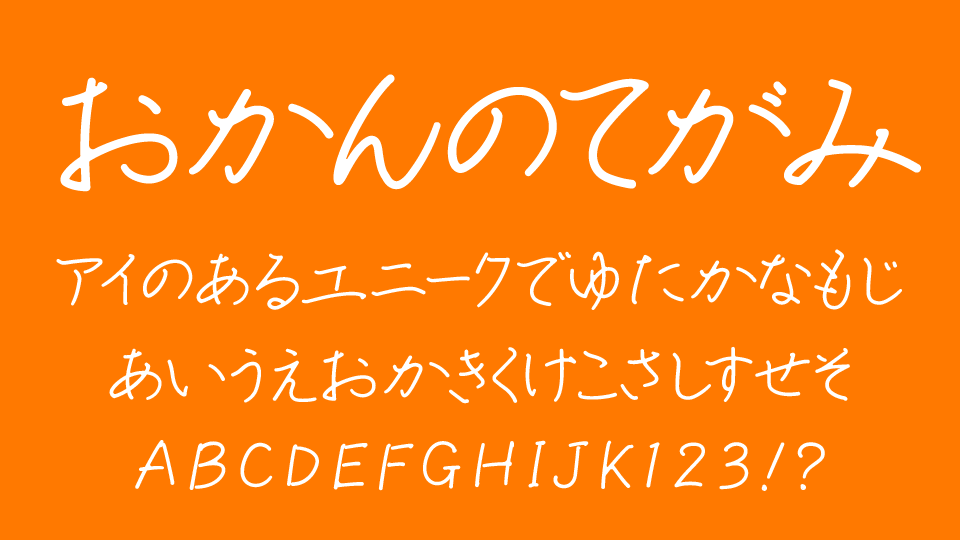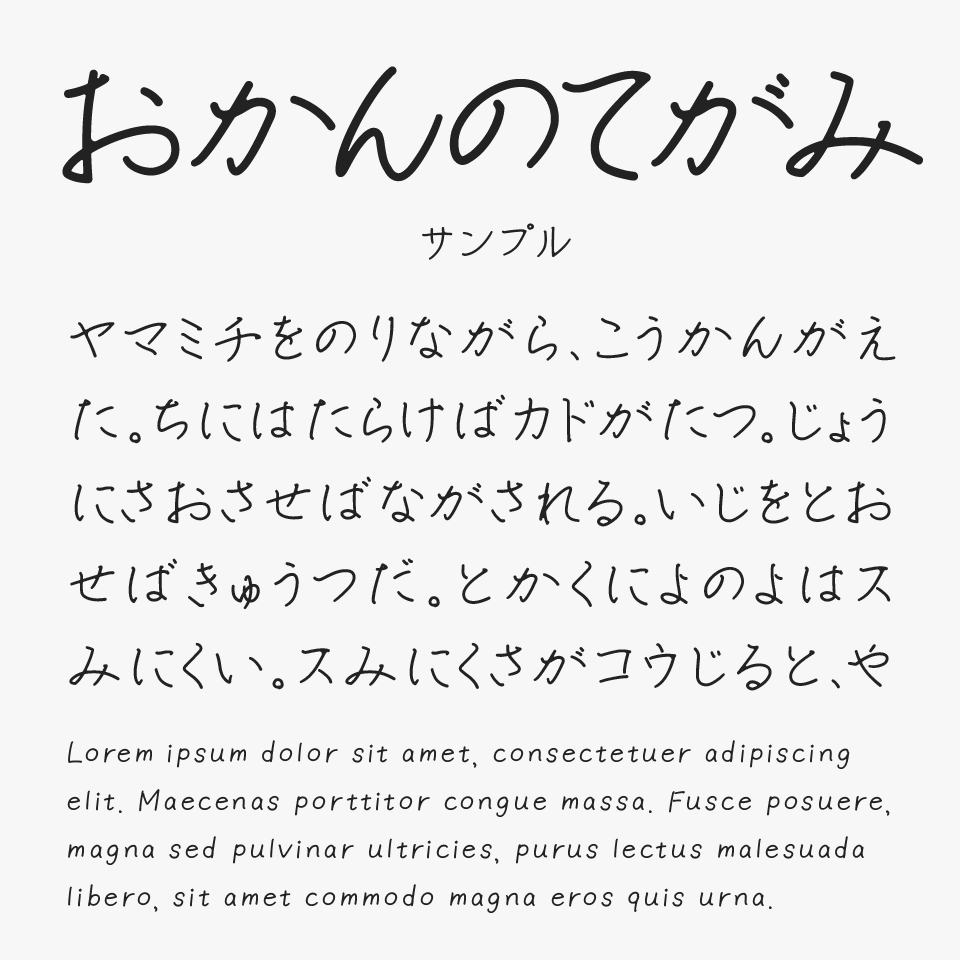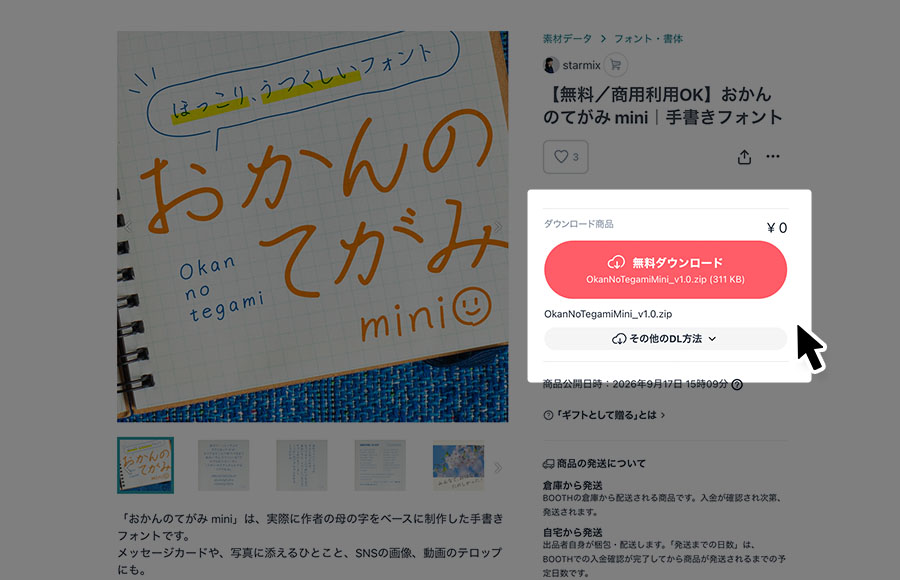
おかんのてがみ
おかんのてがみフォントは、作者のstarmixさんのお母さまが実際に書いた文字をベースに制作された、整った筆跡が特徴の手書きフォントです。
細めの線にはほどよい揺らぎがあり、文字の大きさや傾きも少しずつ異なるため、リアルな人がペンで書いたような自然な表情が感じられるフォントです。
整いすぎていない素朴さがありながらも読みやすく、どこか懐かしく、身近な人から届いた手紙のような温かさを感じるフォントです。
手紙やメッセージカード、日記、エッセイ、SNS投稿、漫画のセリフなど、言葉を身近に感じさせたいデザインにぴったりなフォントです。かしこまった印象にならないため、日常のひとことや家族をテーマにしたコンテンツにもよく合います。文字を飾るというより、気持ちをそのまま届けたいときに使いやすいフォントです。